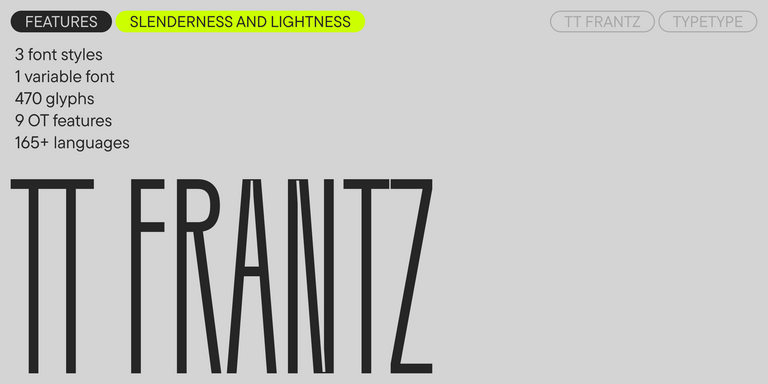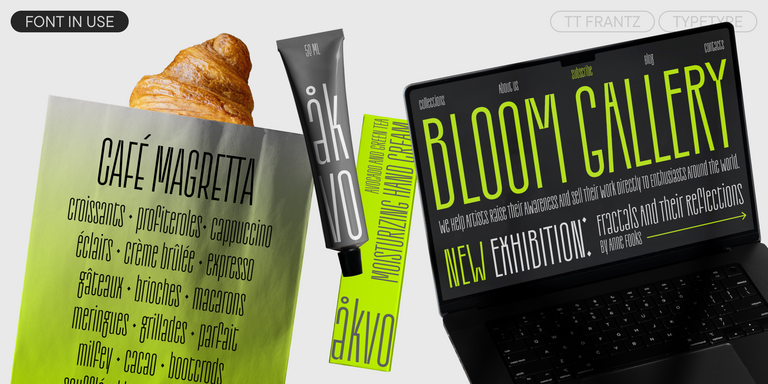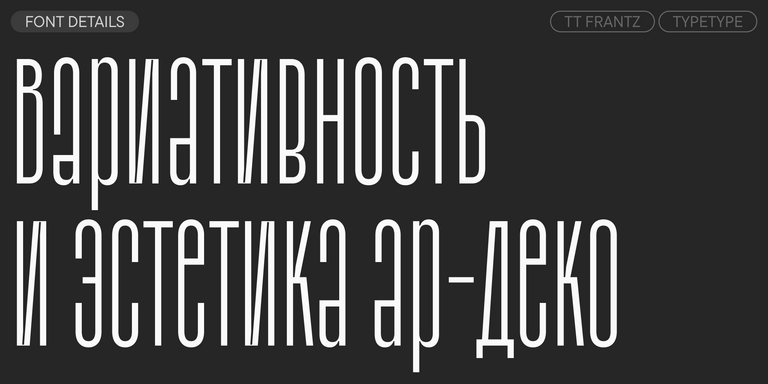
TT Supermolot Neue — технологичный модульный гротеск с футуристическим настроением и мощным функционалом. Яркость его характера сочетается с универсальностью применения.
В TT Frantz можно найти небольшие отсылки в эстетике арт-деко, которые выражены в сильно заниженной или наоборот сильно завышенной талии у букв. Кроме того, в зависимости от положения ползунка регулировки оси, у некоторых букв изменяется закрытость апертуры.
TT Firs Neue — скандинавский гротеск, сочетающий выразительные графические элементы с универсальностью использования. Мы проанализировали каждый контур и графический элемент. Пересобрали шрифт заново, чтобы сохранить лучшее и исправить необходимое.
TT Wellingtons — это гуманистический гротеск, формы которого отсылают к движению ширококонечного пера. Пластичные линии букв обновлённой гарнитуры, присущие английским гуманистическим шрифтам XX века, выглядят актуально и живо в современных дизайнерских проектах.
TT Lakes Neue в версии 2.0 — продолжение геометрического гротеска, вдохновлённого финским функционализмом. Новая версия предоставляет больше возможностей, ведь мы не только увеличили кассовый состав и улучшили шрифт технически, но и доработали его визуальный характер.
TT Rounds Neue — гротеск со скругленными формами. В тонких начертаниях шрифт выглядит довольно минималистично и нейтрально: скругленные окончания штрихов становятся практически незаметными, на первый план выходят плавные линии.
TT Autonomous — современный брутальный технологичный гротеск. Основной визуальной характеристикой гарнитуры является заметная сквадраченность знаков и угловатое внутреннее пространство.
TT Backwards Sans — это узкий гротеск, пластичностью своих знаков отсылающий нас в книжное оформление конца 70-х — начала 80-х годов и выполненный с учетом использования в маленьком размере текста. Магазинные вывески, постеры и плакаты, книжное оформление — вот где мы черпали вдохновение для нашего проекта.
Первоначально идея шрифтового семейства TT Milks заключалась в том, чтобы создать коллекцию шрифтов для использования в упаковке и брендинге молочной продукции.
TT Prosto Sans является шрифтовой гарнитурой на любой жизненный случай. Благодаря современным открытым гротескным формам, вы можете использовать гарнитуру почти для любой задачи.